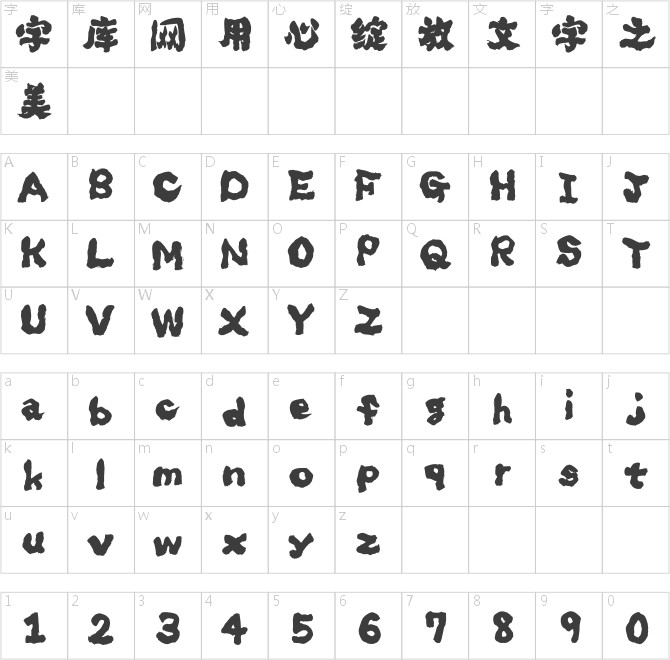
字體名稱: 方正白舟魂心體
方正白舟魂心體
方正白舟魂心體介紹
方正白舟魂心體是一款傾注全身力量書寫的字體,由慣用右手的書法家使用左手書寫制作的,用筆震顫曲折,仿佛一條蜿蜒的河流,在筆鋒處留有點墨,更顯深邃悠遠。方正白舟魂心體筆畫極粗,結構有緊有放、堅實有力,如果在大字號的標題字場合下使用,能讓人切實感受到那種充滿人情味的力量感。這款字體的原始字符由藤本惠書寫創作而成。